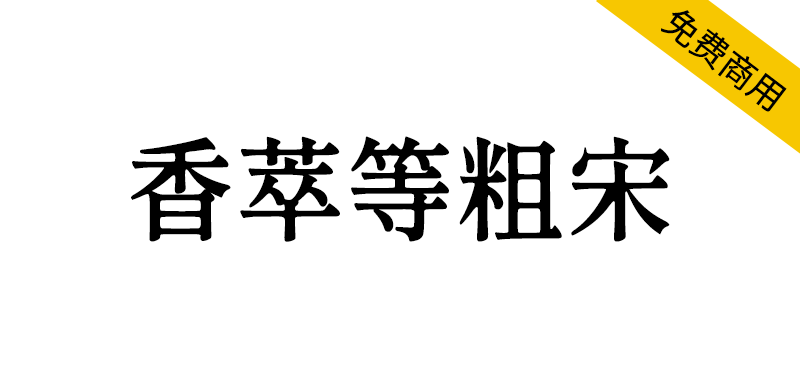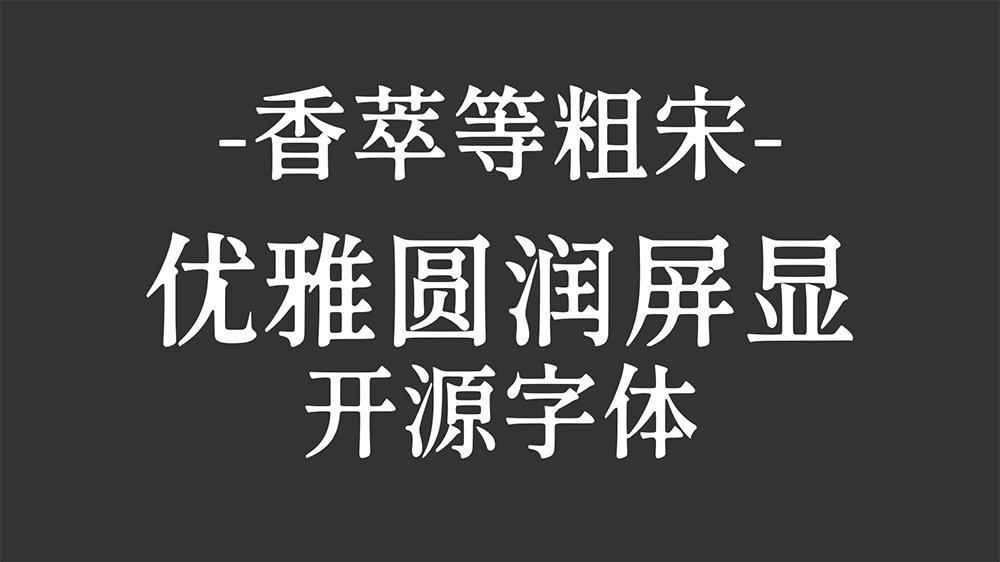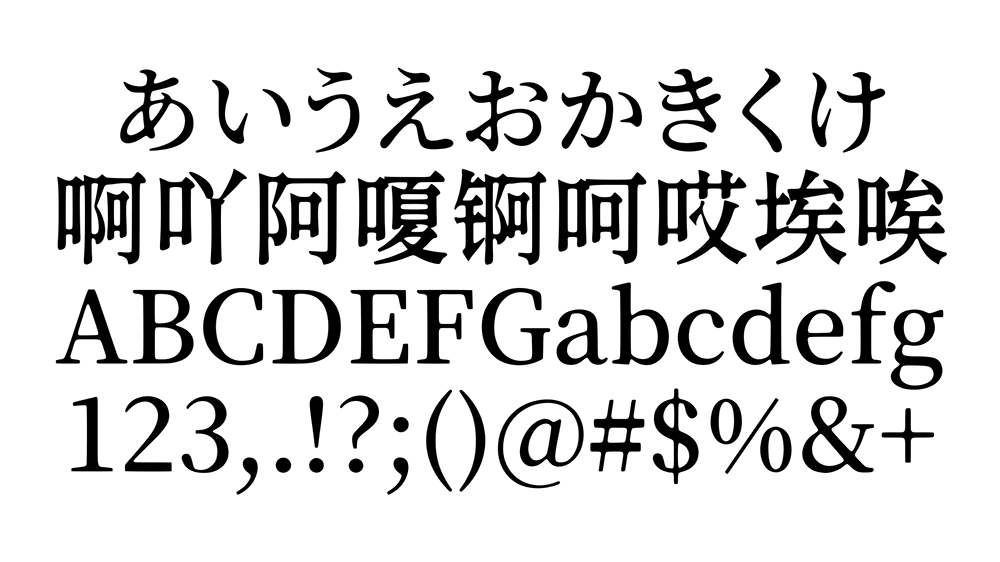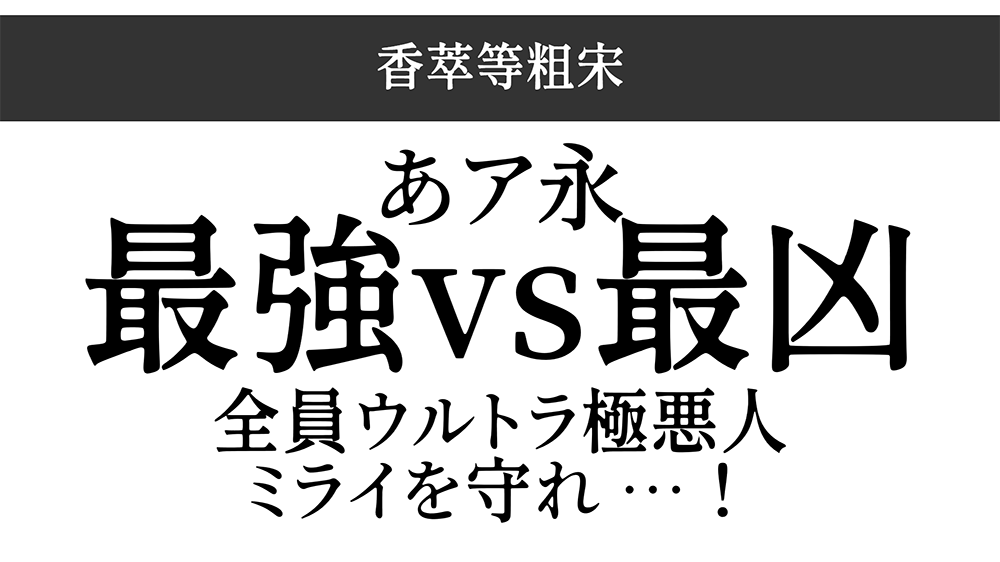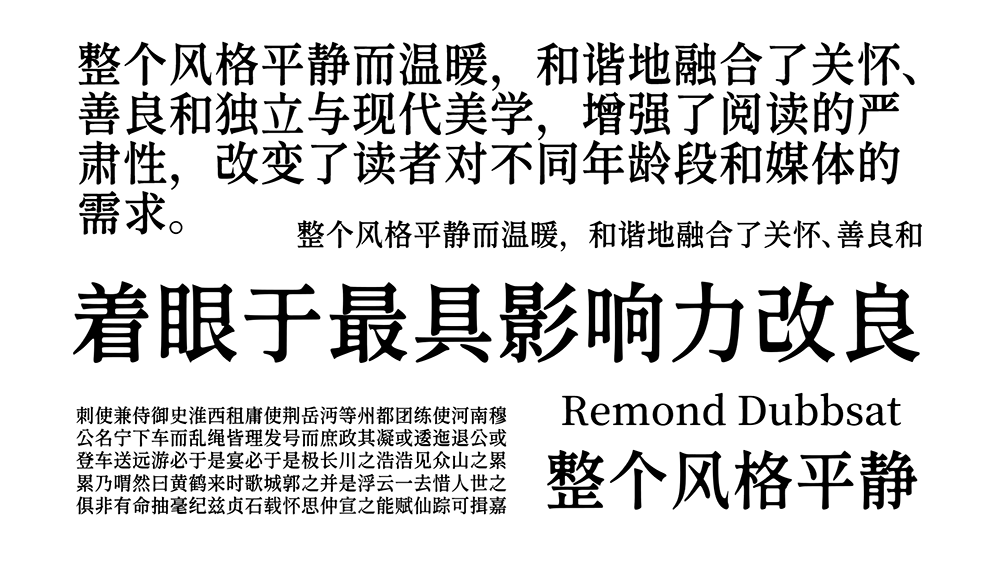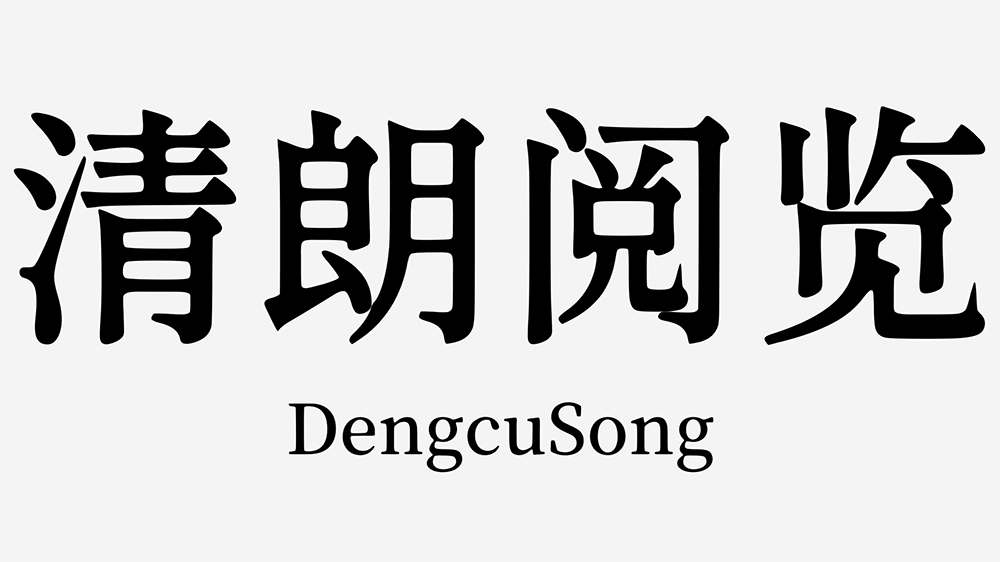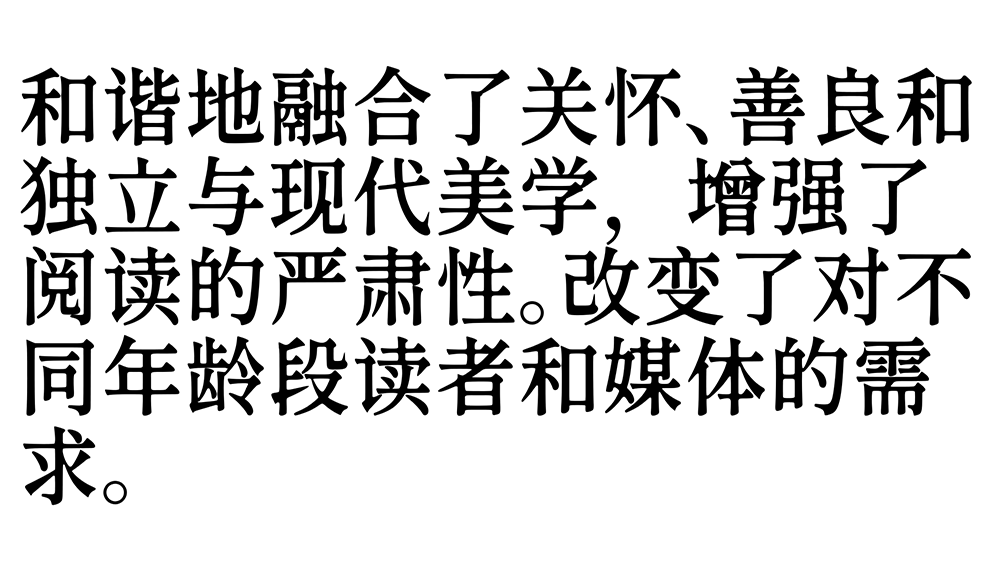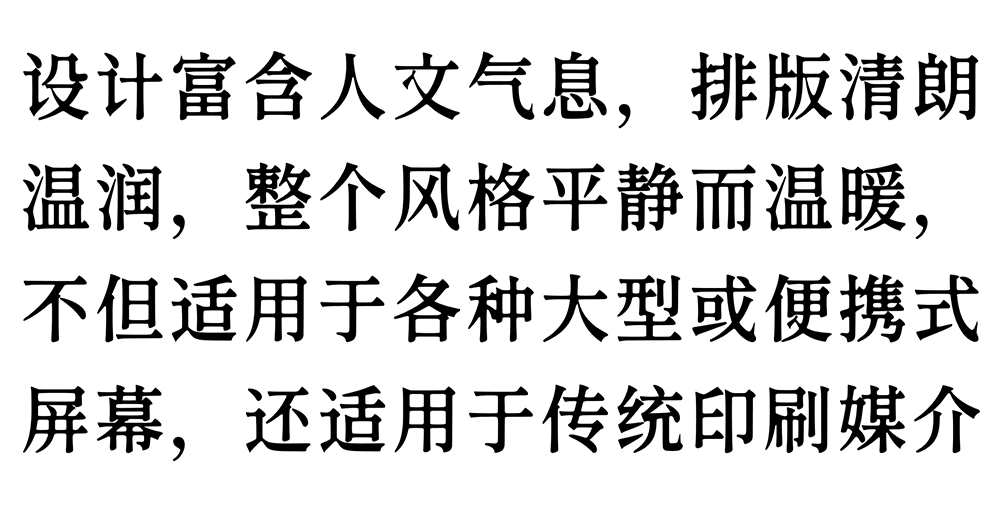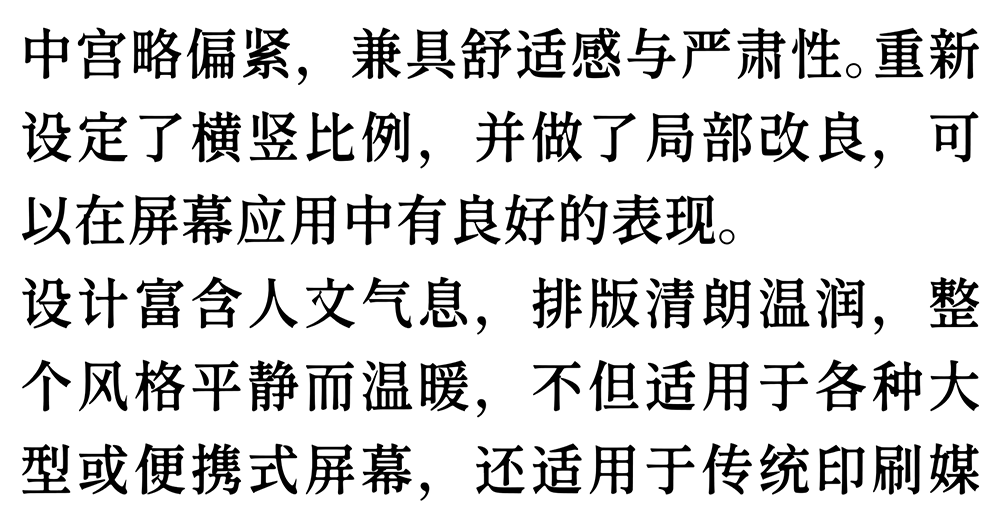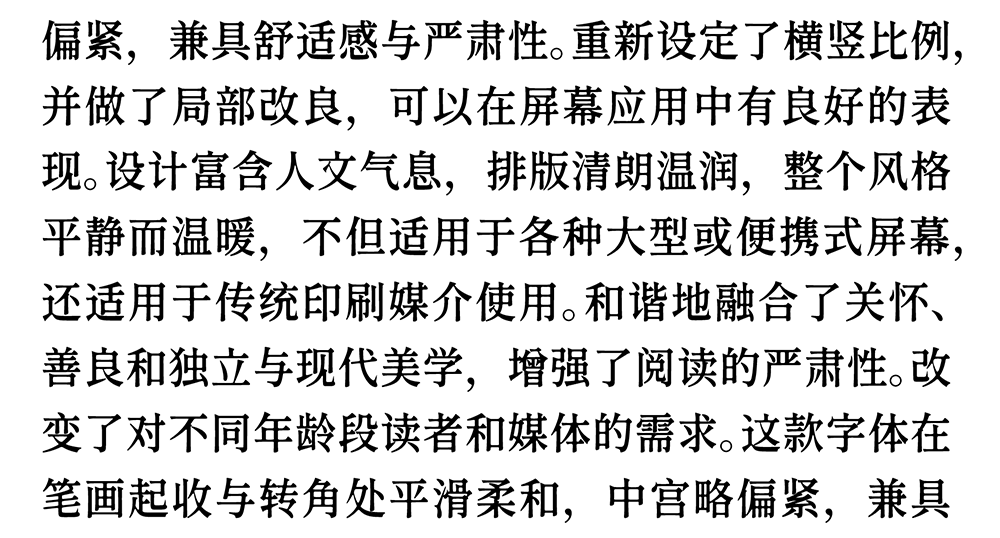
【香萃等粗宋】优雅圆润的开源屏显宋体字体
还在为屏幕字体过于生硬而烦恼?这款香萃等粗宋字体或许正是你需要的答案。作为开源字体新秀,它在起笔转折处采用优雅圆润设计,中宫收紧的结构兼顾阅读舒适度与专业感。特别优化了横竖比例,在各类屏幕上都能呈现清晰锐利的显示效果,同时完美适配印刷媒介。更特别的是,它巧妙融合新旧字形规范,让传统韵味与现代实用性相得益彰。
【香萃等粗宋】优雅圆润的开源屏显宋体字体
香萃等粗宋是一款开源中文字体项目,这款字体在笔画起收与转角处平滑柔和,中宫略偏紧,兼具舒适感与严肃性。重新设定了横竖比例,并做了局部改良,可以在屏幕应用中有良好的表现。
设计富含人文气息,排版清朗温润,整个风格平静而温暖,不但适用于各种大型或便携式屏幕,还适用于传统印刷媒介使用。
对于含有旧字形的汉字,除“浅残践劲茎径禅蝉惮箪莽蟒类器”等字使用中国大陆规范字形,其余使用旧字形。